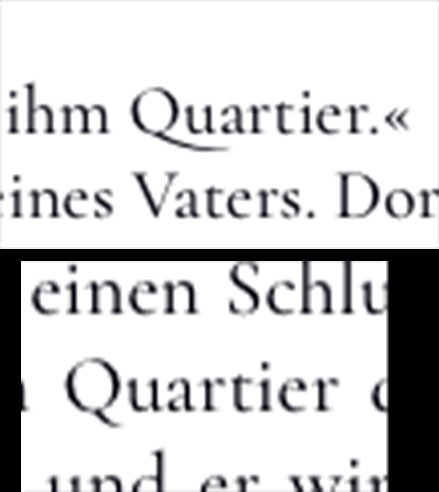
[Mitglied Schr…] Geschrieben Januar 20, 2021 Teilen Geschrieben Januar 20, 2021 Hallo zusammen, ich hoffe, dass hier jemand weiß, was ich entweder falsch mache oder was mit meinem Programm nicht stimmt. Und zwar arbeite ich mit QuarkXpress 15 an einem Mac. Der Buchsatz läuft super, nur spielen mir die Ligaturen einen Streich. Ich habe diese aktiviert, jedoch fehlen einige an manchen Stellen. Wie kann das sein, dass z. B. nicht immer eine Ligatur am Q erzeugt wird? Ich habe alles geprüft und die Ligatur wird als aktiv im gesamten Text angezeigt, sowie in den ausgewählten Wörtern in denen sie fehlen. Gibt es da einen Trick wie ich es eventuell erzwinge? Ich danke euch. Liebe Grüße Schreibfee Link zu diesem Kommentar
[Mitglied Erwi…] Geschrieben Januar 20, 2021 Teilen Geschrieben Januar 20, 2021 Fehlen alle Q-Ligaturen oder fehlen diese nur manchmal? Nicht viele Schriften haben auch wirklich Q-Ligaturen. Link zu diesem Kommentar
[Mitglied Schr…] Geschrieben Januar 20, 2021 Themen-Ersteller Teilen Geschrieben Januar 20, 2021 vor 6 Minuten schrieb Erwin Krump: Fehlen alle Q-Ligaturen oder fehlen diese nur manchmal? Nicht viele Schriften haben auch wirklich Q-Ligaturen. Diese fehlen nur manchmal. Teilweise hat QXP diese erzeugt. Ich hänge mal ein Bild bei. Link zu diesem Kommentar
[Mitglied 4c22…] Geschrieben Januar 20, 2021 Teilen Geschrieben Januar 20, 2021 Verwendest du Formatvorlagen*, in denen die Ligaturen abgewählt sind? (*Keine Ahnung, wie die bei Quark heißen, vielleicht auch Absatzstilvorlagen …) Link zu diesem Kommentar
[Mitglied Schr…] Geschrieben Januar 20, 2021 Themen-Ersteller Teilen Geschrieben Januar 20, 2021 vor 10 Minuten schrieb bertel: Verwendest du Formatvorlagen*, in denen die Ligaturen abgewählt sind? (*Keine Ahnung, wie die bei Quark heißen, vielleicht auch Absatzstilvorlagen …) Ich verwende die "Normal". Bin kein Ass in QXP, bringe mir alles selbst bei. 🙈 Anbei einen Screenshot. Link zu diesem Kommentar
[Mitglied 4c22…] Geschrieben Januar 20, 2021 Teilen Geschrieben Januar 20, 2021 ok … die Frage ist, wie dieses "normal" definiert ist, ob hier Ligaturen deaktiviert sind. Link zu diesem Kommentar
[Mitglied Erwi…] Geschrieben Januar 20, 2021 Teilen Geschrieben Januar 20, 2021 M. E. handelt es sich hier um keine Ligatur, sondern um eine Formatvariante. Das ist vom Font vorgegeben wie du diese erreichst. Ev. gibt es für dieses alternative "Q" einen Formatsatz (Stylistic Set). Du kannst den Buchstaben auch über die Glyphen-Tabelle auswählen und mit Suchbefehl tauschen. 1 Link zu diesem Kommentar
[Mitglied Klau…] Geschrieben Januar 20, 2021 Teilen Geschrieben Januar 20, 2021 Das »Q« ist ja keine Ligatur. Die unterschiedlichen Formen verbergen sich entweder unter »Formatvarianten« (z.B. bei der Vollkorn) oder unter «kontexbedingte Varianten« (z.B. bei der Ysabeau) und/oder sind u.U. über Stilsets abrufbar. Beste Grüße Link zu diesem Kommentar
[Mitglied Schr…] Geschrieben Januar 20, 2021 Themen-Ersteller Teilen Geschrieben Januar 20, 2021 Ich danke euch allen für die zahlreichen Tipps. Zwar haben mich diese nicht direkt zum Problem geführt, aber dadurch habe ich das Feld "Format übertragen" gefunden. So habe ich dieses angeklickt, danach den Buchstaben Q gesucht und auf die fehlende Ligatur gedrückt. Et voila schon hat Quark die gewünschte Ligatur erzeugt. Tausend Dank an euch allen! 😄 Link zu diesem Kommentar
[Mitglied Klau…] Geschrieben Januar 20, 2021 Teilen Geschrieben Januar 20, 2021 Ich will jetzt nicht kleine Trockenfrüchte ausscheiden, aber »Q« ist keine Ligatur. Falsche Begriffe führen zu erschwerter Fehlersuche. Dehalb bitte einfach mal schauen, was Du da mit »Format übertragen« übertragen hast. Beste Grüße Link zu diesem Kommentar
[Mitglied Schr…] Geschrieben Januar 20, 2021 Themen-Ersteller Teilen Geschrieben Januar 20, 2021 vor 5 Minuten schrieb KlausWehling: Ich will jetzt nicht kleine Trockenfrüchte ausscheiden, aber »Q« ist keine Ligatur. Falsche Begriffe führen zu erschwerter Fehlersuche. Dehalb bitte einfach mal schauen, was Du da mit »Format übertragen« übertragen hast. Beste Grüße Danke dir. Ich habe mir den Text angeschaut. Es hat sich an den restlichen Einstellungen nichts bei mir verändert. Wie werden dann solche Buchstaben genannt wenn sie entsprechend (also wie Ligaturen von der Optik) genannt? Link zu diesem Kommentar
[Mitglied Diet…] Geschrieben Januar 20, 2021 Teilen Geschrieben Januar 20, 2021 vor 7 Minuten schrieb Schreibfee: Wie werden dann solche Buchstaben genannt wenn sie entsprechend (also wie Ligaturen von der Optik) genannt? Das hat Klaus vor 45 Minuten erklärt. Link zu diesem Kommentar
[Mitglied catf…] Geschrieben Januar 21, 2021 Teilen Geschrieben Januar 21, 2021 Das Q ruft ja geradezu zum OpenType-Spieltrieb auf: 1. Kommt das u hinter das Q = Qu-Ligatur. 2. Folgt hinter Q ein irgend ein Kleinbuchstabe, wird eine verlängerte Variante des Q gesetzt. 3. ..., so lange der Folgebuchstabe keine kollidierende Unterlänge hat, 4. Folgen noch weitere Kleinbuchstaben,wird das Q nochmals durch eine längere Version ersetzt. Dies kann dann auch über eine bestimmte Zahl an Buchstaben gelten, z.B. Q wird bis zum 4. Buchstaben stufenweise verlängert. 5 . Folgt hinter Q ein Kleinbuchstabe, wird der Q-Bogen gekappt,und der folgende Kleinbuchstabe durch eine Version mit dem Rest des Q-Bogens ersetzt. 6, Folgt ein weiterer Buchstabe werden die zwischen Q und dem letzten Buchstaben des Wortes alle durch eine unterstrichene Version, der den Bogenanfang des Q mit dem Bogelschluss unter dem letzten Buchstaben verbindet. Link zu diesem Kommentar